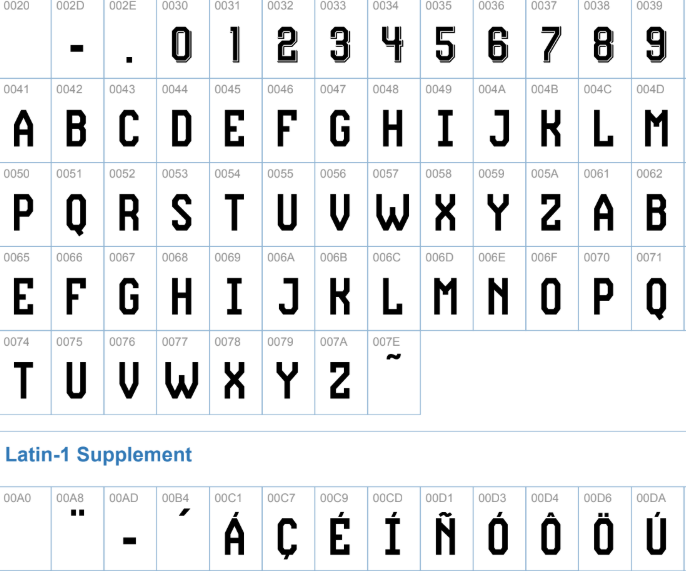
O Gigante da Colina entrou em campo na temporada 2023 vestindo a tradição e a tecnologia da Kappa. Para designers, estamparias e torcedores que desejam personalizar seus mantos com fidelidade total, trazemos hoje o arquivo essencial: a tipografia oficial utilizada nos uniformes do Vasco da Gama.
Esta fonte foi peça fundamental na identidade visual do clube durante o Brasileirão e demais competições, marcando presença tanto na clássica camisa negra com a faixa diagonal quanto no uniforme branco. Se você trabalha com personalização de camisas de futebol ou criação de artes digitais, ter este arquivo em sua biblioteca é obrigatório.
Estilo Visual e Identidade
A tipografia desenvolvida pela Kappa para o Vasco em 2023 aposta em um visual moderno e limpo, mas sem perder a imponência que o clube exige. Diferente de fontes excessivamente arredondadas, ela apresenta cortes geométricos precisos e uma espessura (bold) que garante excelente legibilidade à distância — essencial para a visualização de nomes e números nas transmissões e no estádio.
É uma fonte que transmite solidez e agressividade esportiva, harmonizando perfeitamente com a Cruz de Malta. Ela é ideal para recriar os nomes de ídolos da temporada ou para personalizar camisas de torcida com nomes próprios, mantendo o padrão oficial de loja.